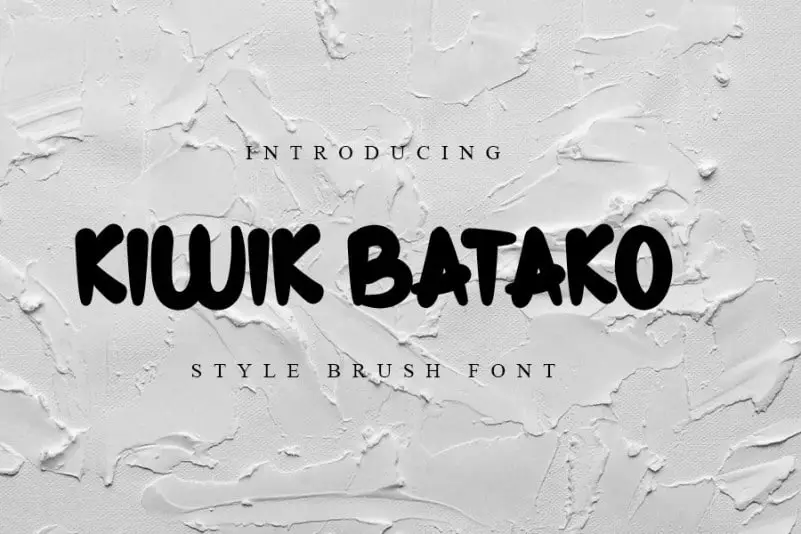
Kiwik Batako Display Font é uma fonte ideal para aqueles que buscam uma fusão perfeita entre a elegância do calligrafia e o frescor contemporâneo. Seu design fluido e alegre mantém seus elementos chamuscados, enquanto inspira criatividade com sua versatilidade impressionante. Ideal tanto para logotipos e letras de título quanto para cartazes e materiais de escritório, essa fonte é perfeita para pessoas que gostam de inovar em suas ideias. Em um mundo sempre em movimento, Kiwik Batako Display continua a desfrutar de seu estilo sofisticado e aposta no novo enquanto se conecta com sua base chamuscada. É uma escolha inteligente para qualquer designer buscando adicionar um toque único à sua próxima criação.